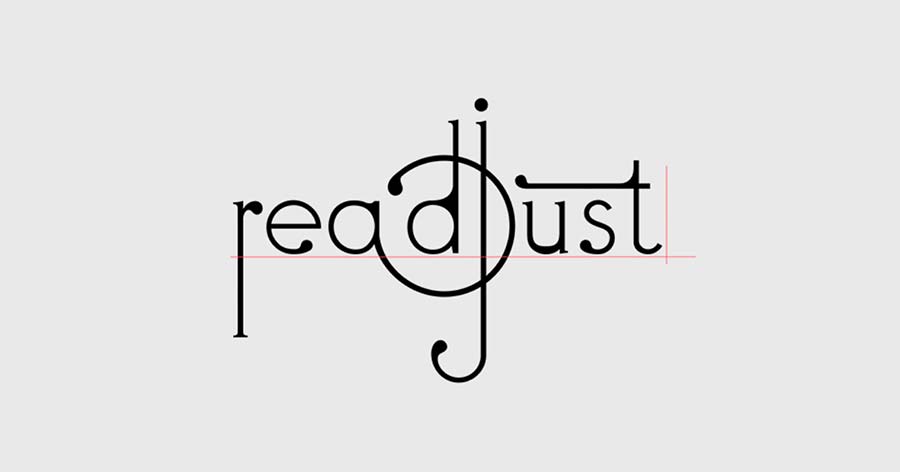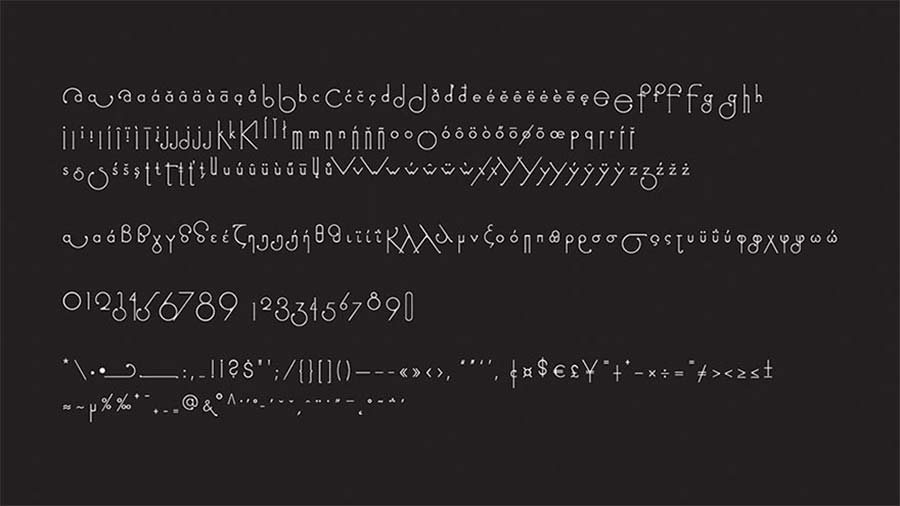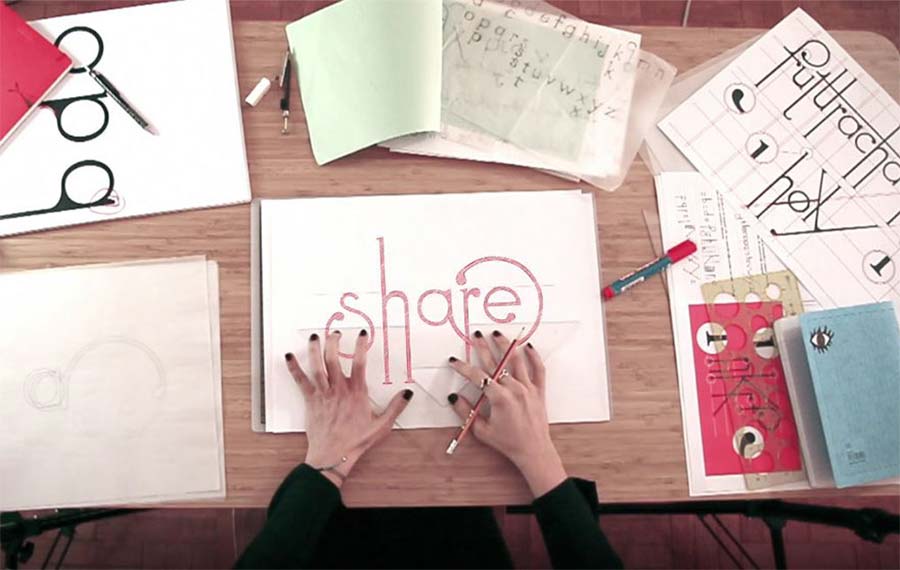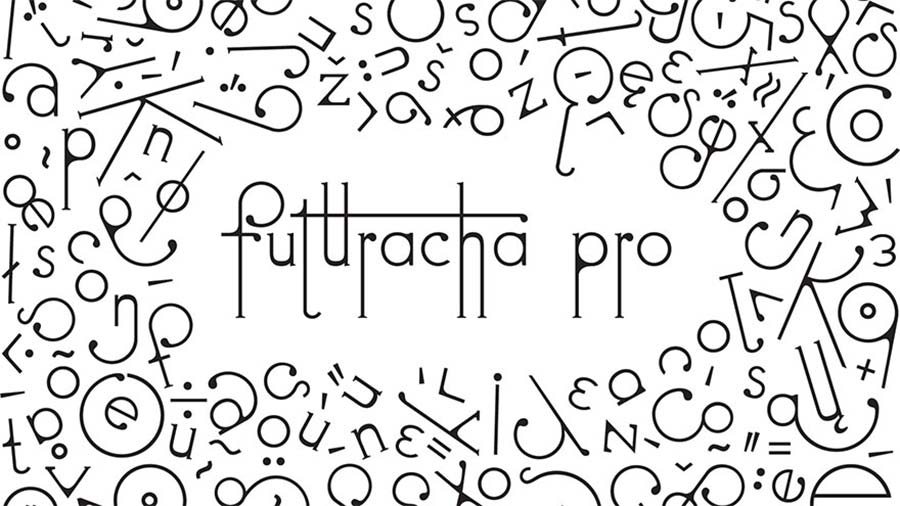
Schriftart passt sich beim Schreiben der Buchstabenfolge an Futuracha-Pro-Font-readjusts-itself_01
Wenn ich Schriftarten durchforste, hatte ich schon häufig diesen Moment, bei dem ich mich in ein gezeigtes Vorschauwort verliebte, weil die Buchstaben so schön ineinander griffen. Aber schnell stellt man fest, dass das eben auch nur in dieser Konstellation schön aussieht – setzt man das weitgreifende „f“ vor oder hinter einen anderen Buchstaben, wirkt es unpassend. Klar, es ist schwer, sämtliche Möglichkeiten der Schriftsprache vorab durchzudenken – aber „Futuracha Pro“ versucht genau das.
Die Schriftart ändert sich während des Schreibens, je nachdem, welcher Buchstabe vor und hinter welchen anderen gesetzt wird. Und auch wenn die elbenhafte Verschnörkelung jetzt nicht ganz meins ist, ist die Idee und Technik dahinter von der griechischen Design-Agentur Høly durchaus lobenswert.
„Its quirkiness and eccentricity are the two main features that made it one of the most beloved fonts in the whole world. Until today, nobody was able to just sit down and type with it. Featuring various combinations of letters and plenty of playful ligatures, Futuracha Pro gives creative people the opportunity to actually type and create, making their ideas extraordinary and unique!“